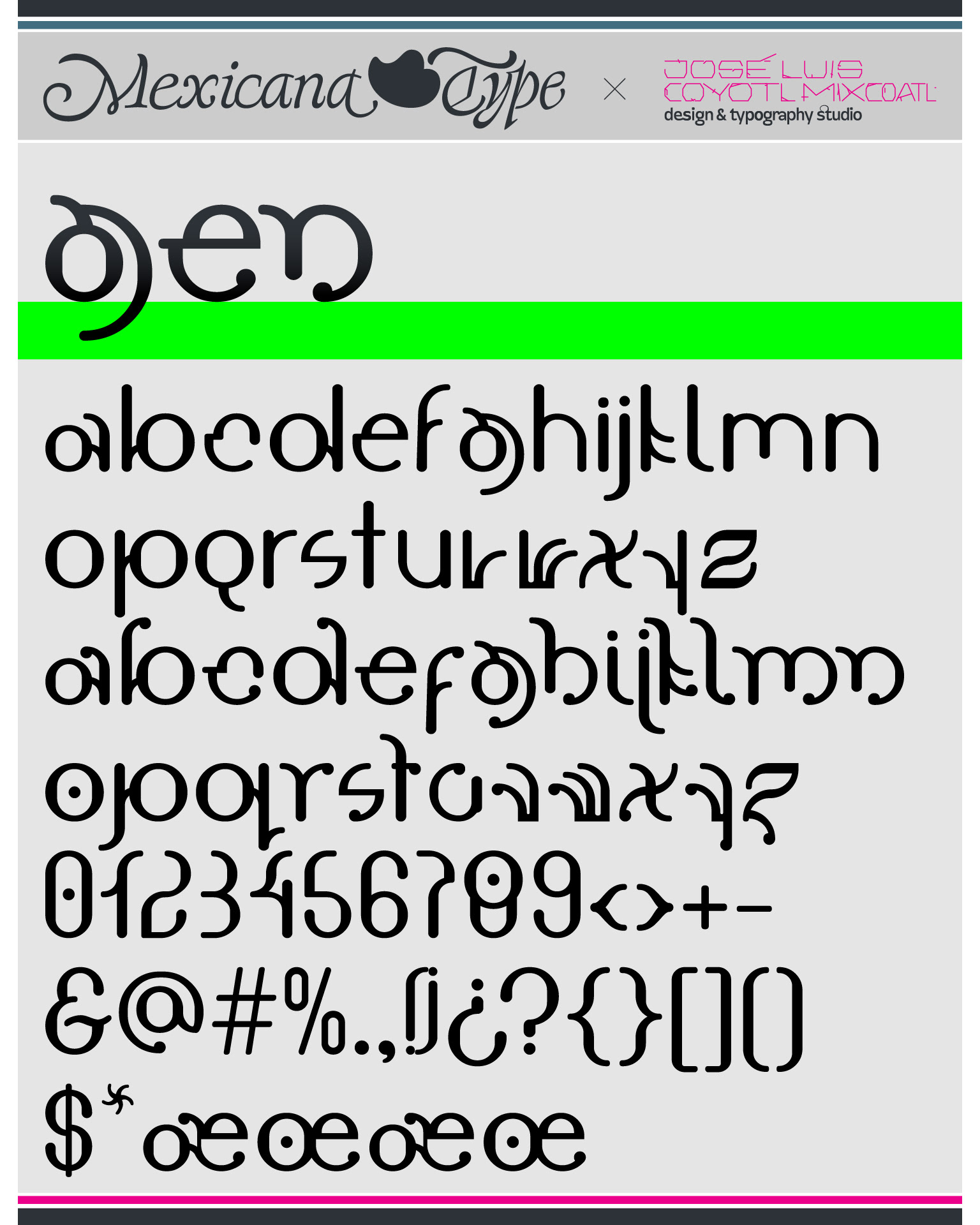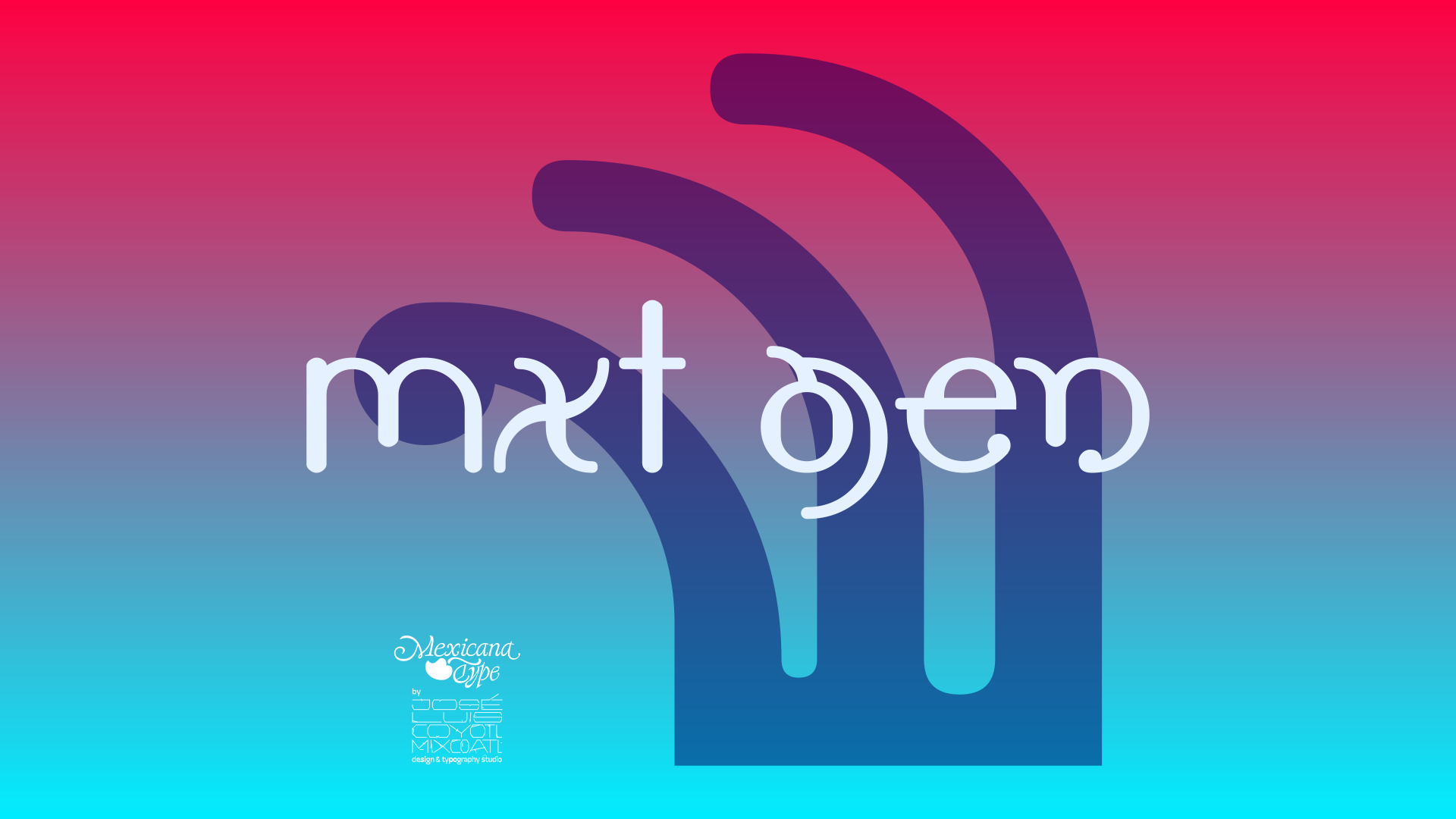
MxT Gen empezó como un ejercicio de letras modulares en mi etapa de estudiante de licenciatura de Diseño Gráfico, fue uno de mis primeros ejercicios de generar una tipografía como tal y ello permitió tener un campo fértil para experimentar en todos los sentidos, empezando por lo formal, pero también en la manera en que fluía como elementos de lectura en su conjunto.
Diseñada como un ejercicio experimental en su estructura general, partiendo de lo modular pero también como una alternativa en sus formas orgánicas, quizá en un sentido desde la lógica Bauhaus pero con un sentido más contemporáneo de finales de los 90's.
En 2005, fue incluida en colaboración con la revista Building Letters como fuente gratuita, como parte del proyecto de ayuda humanitaria Font Aid, para los afectados del tsunami en Asia en 2004.
También incluída en el compilado de tipografías del libro New Typographics en Japón a inicios de la década del 2000.